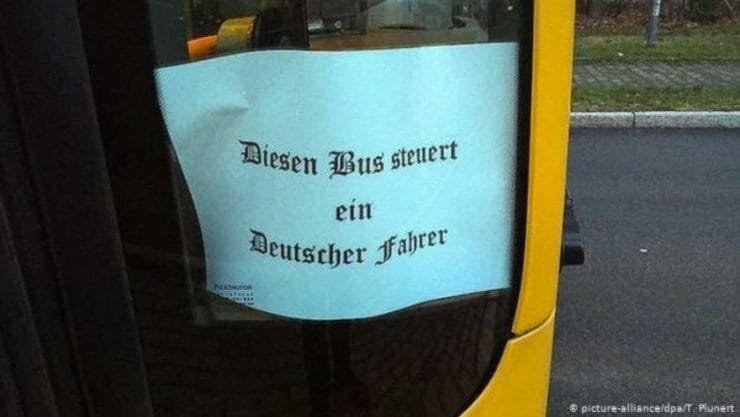
KICKOFF
Eind vorig jaar las ik dit artikel van Arthur Reinders Folmer en deelde op Twitter m'n voornemen om zelf te gaan rommelen met de variable font technologie. Thomas Dahm reageerde met: zullen we anders een workshop organiseren? Sure, why not 😃 Dus benaderden we Arthur met de vraag of hij zo'n workshop zou willen geven en yes, hij was ook aan boord!
Deelnemers waren er in no-time; binnen 10 dagen tijd waren alle 30 beschikbare plekken gevuld. Op 15 februari was het zover en liep GRRR vol met V-font nieuwsgierigen. Arthur heeft in één dag laten zien hoe je in Glyphs een letter variable maakt, hoe je 'm zelfs kleur kunt meegeven en hoe je 'm met CSS en JS in de browser laat animeren. Ik heb zelf natuurlijk ook meegedaan en vond het te gek om eindelijk de basics van VF te leren en om te zetten in een animerend font – ook al was het maar één letter.
De type experimenten van een aantal deelnemers zijn hier te zien. Sommige animeren vanzelf, anderen werken op hover of op window resize.
READING / LISTENING LIST
🔗 Tom De Bruyne—"We moeten de wereld in een betere plek manipuleren" (Glitch podcast) — www.glitch.show
Tom de Bruyne is oprichter van behavioral design agency SUE en weet als geen ander hoe menselijk gedrag in een bepaalde richting kan worden gestuurd. Dat kan een donkere richting zijn of een positieve. Je raadt het al: Tom zet z'n kennis in om mensen de goede kant op te nudgen. Super leuk gesprek met David en Laurens van Glitch.
🔗 A Complete Guide to Links and Buttons — css-tricks.com
Ook ik maak in design vaak geen visueel onderscheid tussen een link en een button. Maar onderwater zijn het twee verschillende dingen. Hoe zit dat ook alweer?
🔗 Variable fonts’ past, present and future, according to Dalton Maag — www.itsnicethat.com
Dalton Maag was een van de eerste typefoundries die variable fonts uitbracht. Hun creative director Bianca Berning vertelt over het ontstaan van de techniek en in welke richting de ontwikkelingen gaan.
🔗 Fraktur (99% Invisible podcast) — 99percentinvisible.org
Als je een tekst een overdreven nationalistisch-Duitse vibe wil geven, dan zet je 'm in de Fraktur. Iedereen kent dit lettertype dan ook als hét nazi-font. Maar wist je dat Adolph Hitler een schijthekel had aan de Fraktur?
IN JE FACE
Broncode
Sterk campagne-idee van de Amsterdamse 72andSunny: in de broncode van een aantal grote websites zijn ascii-portretten te zien van developers die aan die websites hebben gewerkt en die van oorsprong vluchteling waren. Check bijvoorbeeld de broncode van Marktplaats. Dit alles ter promotie van HackYourFuture, een coding school voor vluchtelingen.
Making waves
Studio Output heeft Mixcloud gerestyled en I like it. De verschillende identity-onderdelen ogen los van elkaar niet heel bijzonder, maar de optelsom zorgt voor een sterk Mixcloud gevoel.
MUST: FLORIS DOUMA
Must read
Rework – Jason Fried, oprichter van project management tool Basecamp, vertelt inspirerend in bondige hoofdstukken over hoe je als online onderneming succesvol kunt worden. Hij druist fijn in tegen het bekende start-up/IPO/venture capital 'gesjees'. Verplichte kost voor iedereen die een online zaak wil beginnen maar denkt dat 'ie daar eerst tweeënhalve ton voor moet lenen.
Must see
Podcasts van NPR – Als je nog geen podcast verslaafde bent, maar wel ambities hebt in die richting, begin dan bij de podcasts van de Amerikaanse publieke radio omroep NPR. Stuk voor stuk steengoed en meer dan geschikt als gateway drug :) How I built this, The Indicator, Planet Money & Ted Radio Hour zijn mijn persoonlijke favorieten. Podcasts zijn ook aan te raden als je sportambities hebt, maar het sporten zelf eigenlijk te saai vindt.
Must use
DaisyDisk – Voor als je harde schijf bijna vol zit, maar je weet niet waar je gigabytes precies gebleven zijn. DaisyDisk visualiseert je harde schijf op een mooie en slimme manier zodat je gemakkelijk op kunt sporen waar je nog wat ruimte kunt vrijmaken.
Floris is freelance creative web-developer
UITSLAG HALFVET SURVEY
De vorige keer vroeg ik jullie mening over Halfvet. 65 personen reageerden (13% van de lezers), die de survey in gemiddeld 6:13 minuten invulden. Hier de resultaten 🎉
Als eerste vroeg ik om de nieuwsbrief-onderdelen een cijfer te geven:
Daarna vroeg ik: Wat vind je van de lengte van de nieuwsbrief?
En toen: Hoe heb je Halfvet ontdekt?
Als laatste vroeg ik naar dingen die beter kunnen. Twee zaken werden het meest genoemd: het mag persoonlijker (meer mijn mening, meer over GRRR), en het design kan beter (minder plomp, meer uitgesproken, beter onderscheid tussen de secties). Ik knoop het in m'n oor!
Daarnaast mogen vrouwen meer aan bod komen, kan er meer context bij de Must-persoon, is er behoefte aan een Halfvet podcast en nog een heleboel andere bruikbare suggesties!